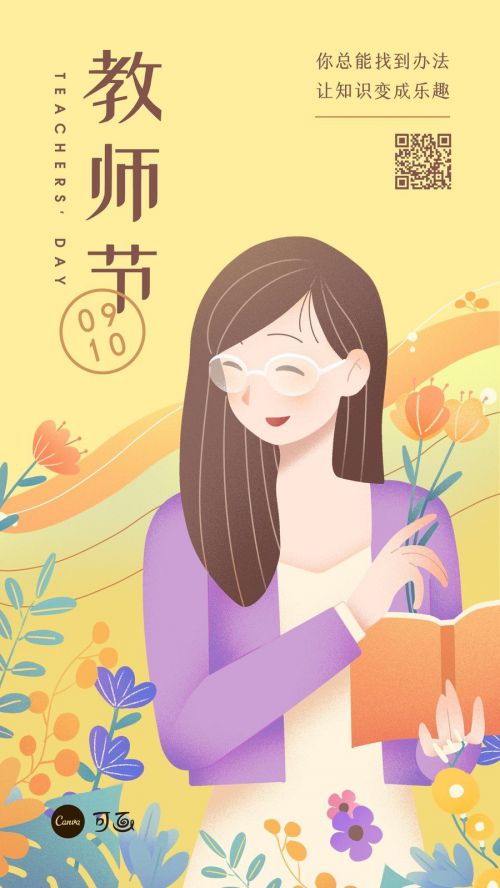
站酷小薇LOGO体
字库品牌: 站酷字体
【站酷小薇LOGO体:免费商用的创意LOGO设计神器】 站酷小薇LOGO体是由站酷字体推出的免费商用创意字体,由设计师李大卫团队打造,不仅是一份饱含父爱的礼物,更填补了免费LOGO设计字体的市场空白。字体以古典端庄与简约优雅为核心风格,兼顾标志设计与标题创作的实用性。 站酷小薇LOGO体字形方正稳重,重心居中,中宫宽博,展现出平衡大气的视觉效果。其笔画设计独特,采用均匀粗度的方头笔触,搭配精致直角装饰元素,笔画间巧妙断开,既保留了利落的现代感,又透着灵秀谦和的古典韵味。 站酷小薇LOGO体支持GB2312编码,收录6763个汉字,适用于品牌标志、广告标题等场景。作为免费商用字体,它兼具设计感与实用性,为设计师提供了高效且富有创意的文字解决方案。